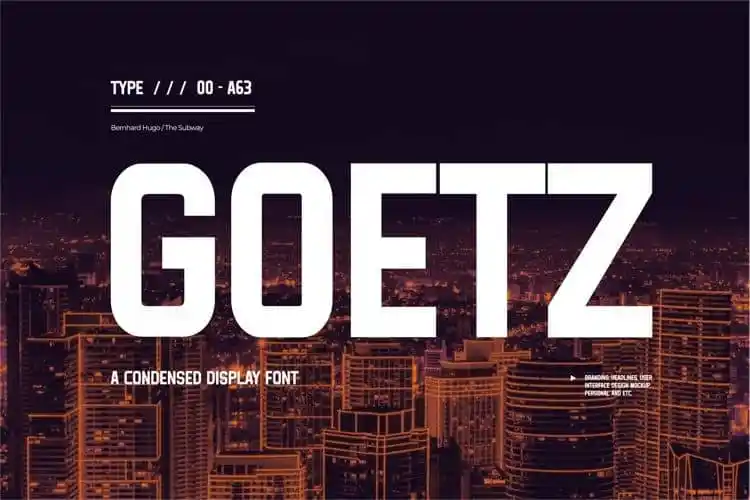
Goetz Display Font – Download Grátis
Goetz Display Font é uma fonte moderna e única criada pela 1995std que traz ao seu design um toque sofisticado e forte, perfeitamente adaptada para aplicações que precisam de um ar acolhedor e confortável tanto para web quanto para papel. Essa fonte capta a atenção com suas formas grandes e redondas, especialmente adequada para temas como tecnologia, industrialização e esportes. Suas características em letras maiúsculas e estreitas são perfeitas para uso em logomarcas e identidades visuais, headlines, cartazes, publicidade, marketing e muito mais. Seu design é atraente, criando um ambiente amigável que encoraja uma experiência visual agradável em qualquer aplicação onde seja usada. Goetz Display Font traz elegância e força para seu projeto, tornando-o chamativo e memorável.